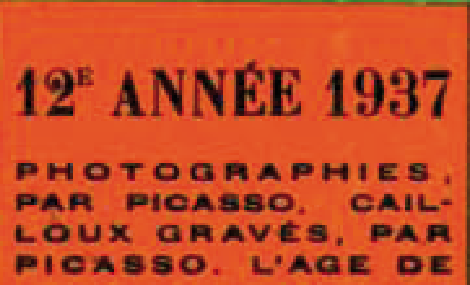
Zwei Schriften gesucht (30er Jahre Frankreich)
bin mal wieder auf der Suche nach zwei Schriften. Leider nur ein schlecht aufgelöstes Bild davon.
Jemand eine Idee?
Möglicherweise hilft jenes Bild bei der Suche:
ich hab mal experimentiert und glaube, es könnte dich bei der Serifenschrift um eine Variante der Bodoni handeln.
Allerdings kann ich nirgends diese speziell geschwungene "2" finden.